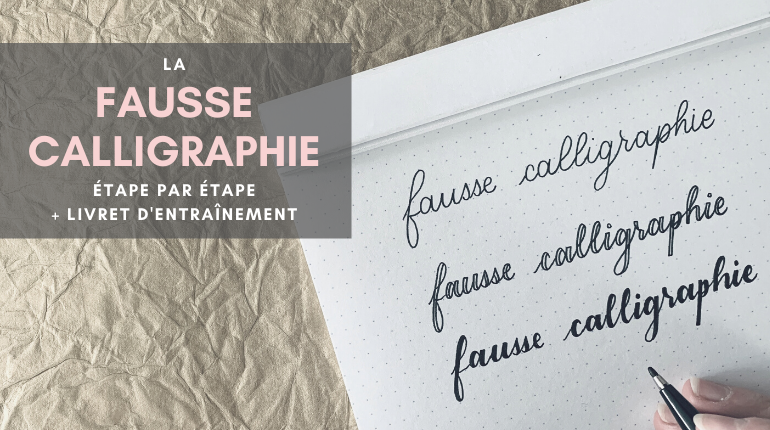
Pourquoi fausse ?
La différence principale entre la fausse calligraphie et la calligraphie dite « normale », c’est les outils utilisés.
La fausse calligraphie est considérée comme plus simple et moins chère car elle ne nécessite pas l’achat de nouveaux outils. Vous pouvez utiliser les stylos, feutres et crayons que vous utilisez tous les jours pour retrouver les pleins et déliés de la calligraphie.
L’autre raison qui rend la fausse calligraphie aussi populaire, c’est le fait qu’elle puisse être utilisée sur des surfaces beaucoup plus variées que les feutres pinceaux ou la plume. Grâce à cette technique vous pourrez notamment faire de la calligraphie sur vitre, ardoises, miroirs, bois, etc.
Comprendre la base de la calligraphie
Le concept le plus important en calligraphie (quelle soit fausse ou non) ce sont les pleins et les déliés. Les parties les plus fines et les plus épaisses de vos lettres correspondent à un mouvement vers le haut ou à un mouvement vers le bas.
Principe de base :
– Les traits qui montent sont fins = déliés
– Les traits qui descendent sont épais = pleins
En calligraphie moderne, la formation de ces traits fins et épais se fait en changeant la pression faite sur le feutre pinceau ou la plume. Le plus on appuie sur le feutre, le plus le trait sera épais.
Cependant en fausse calligraphie, on ajoute manuellement la partie du trait qui est censée être épaisse. On imite simplement ce qui se passerait si on utilisait un feutre pinceau ou une plume. On « fausse » la calligraphie, d’où son nom !
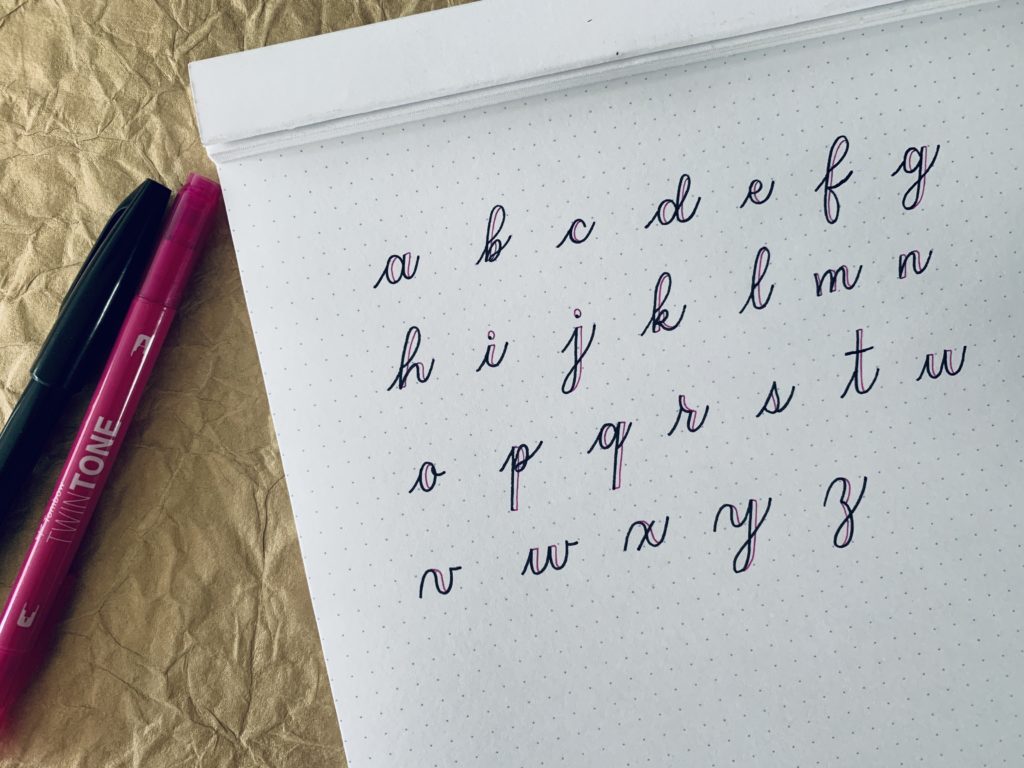
Quels stylos utiliser ?
Vous pouvez utiliser n’importe quel stylo que vous avez à la maison: un crayon à papier, un stylo gel, un surligneur, n’importe quoi !
Personnellement j’utilise soit un crayon à papier, soit un feutre à pointe fine du type Micron 05, Edding 0.7, Artline 0.4 ou Pentel SignPen. Mais ils ne sont en aucun cas indispensables et vous pouvez très bien avoir le même effet sans eux !
P.S: Ne pas utiliser pas de feutres pinceaux ou de plumes.
Etape par étape
- Ecrivez le mot que vous souhaitez travailler
Vous pouvez écrire dans le style que vous souhaitez ou vous pouvez télécharger le livret d’entraînement (en bas de page) dans lequel je vous donne la base de l’alphabet. Assurez-vous d’écrire assez gros et de bien aérer et lier vos lettres sans quoi l’ajout de pleins sera compliqué.
- Créer les pleins et déliés
Pour créer cette différenciation entre les pleins et les déliés, il vous suffit d’ajouter du poids à tous les pleins (traits descendants) en étant le plus régulier possible.
- Remplir les pleins
Vous pouvez choisir de remplir les pleins ou non afin de garantir cet effet « faux ». Et voilà un effet garanti sans feutre pinceau ou plume !